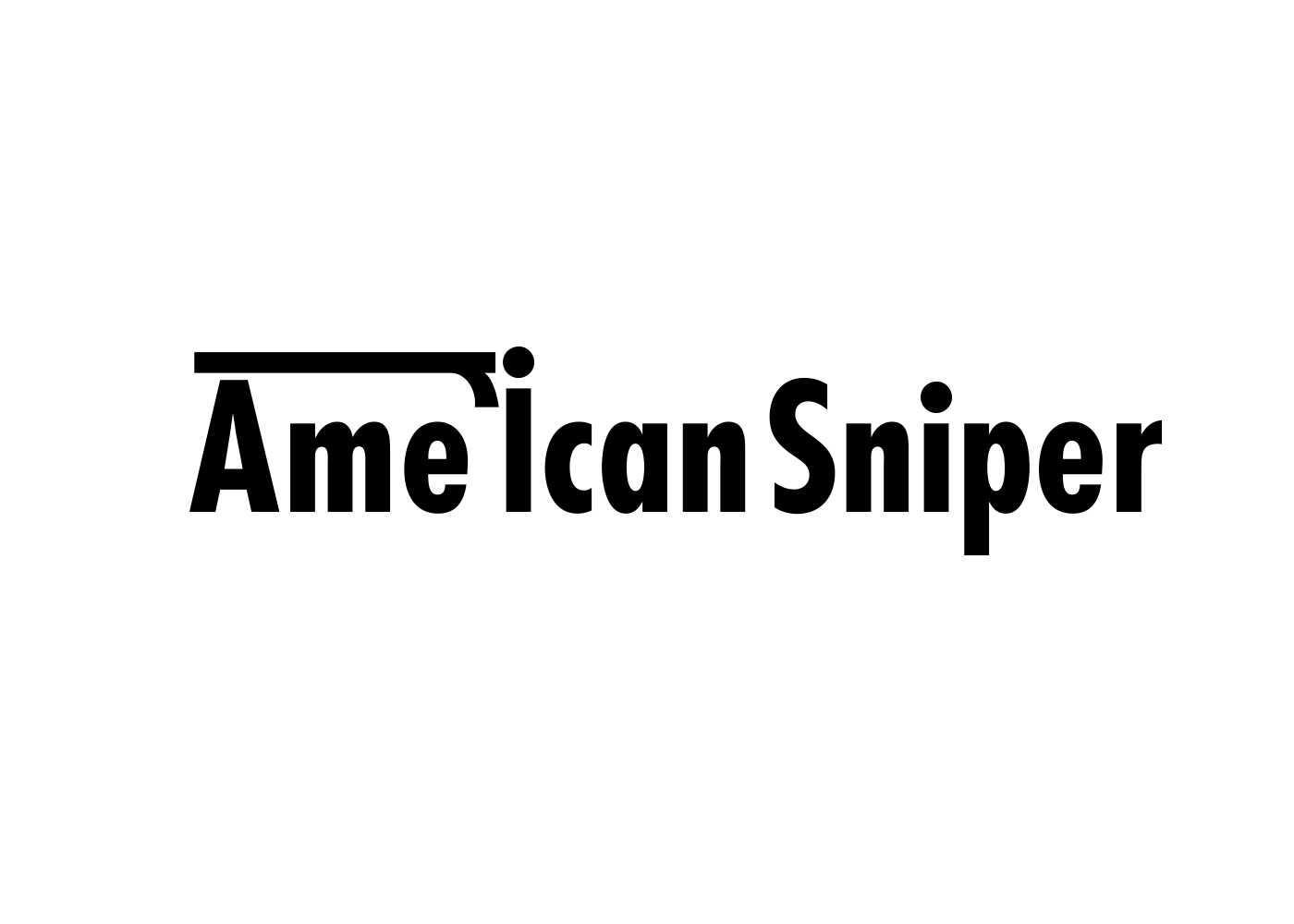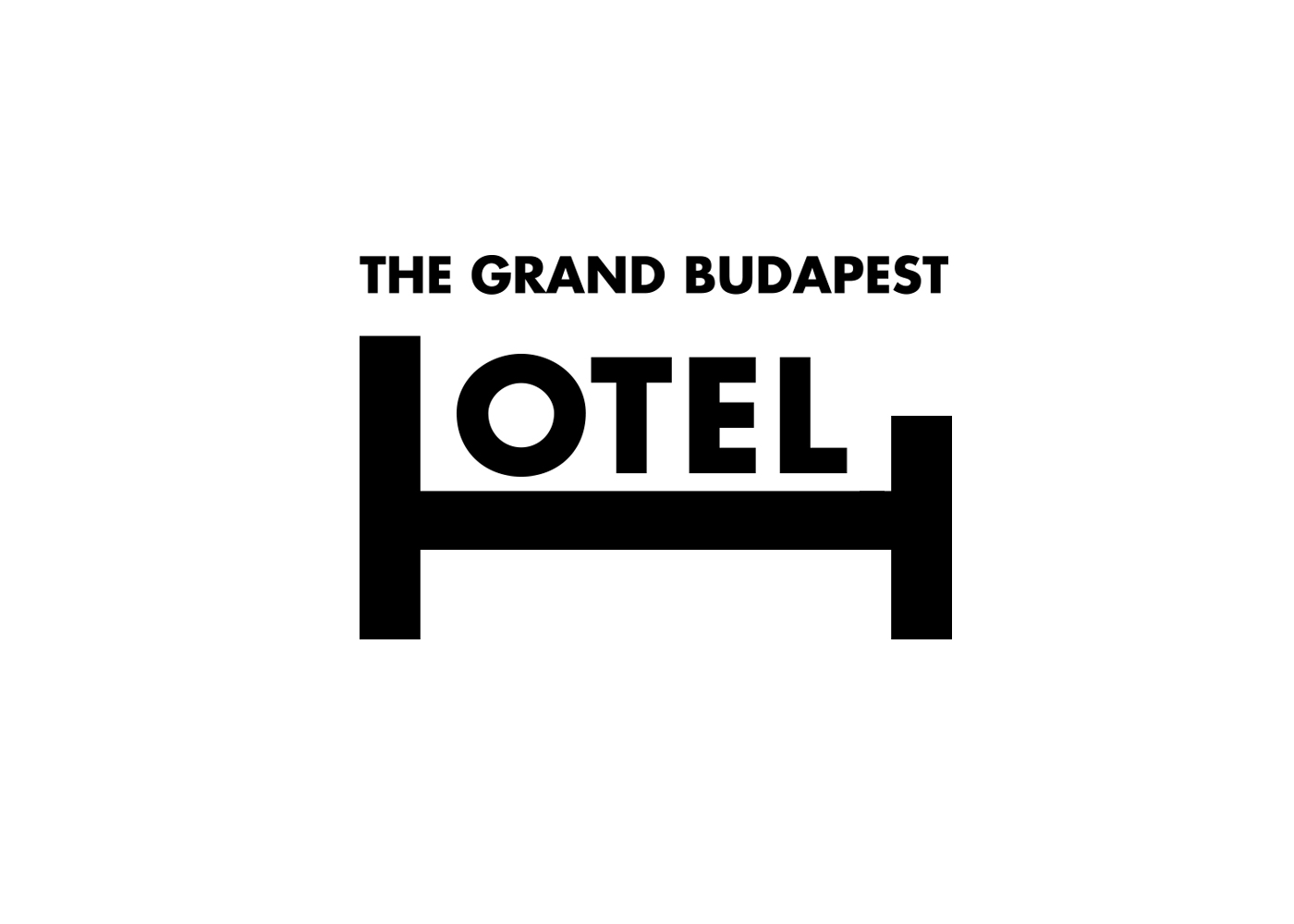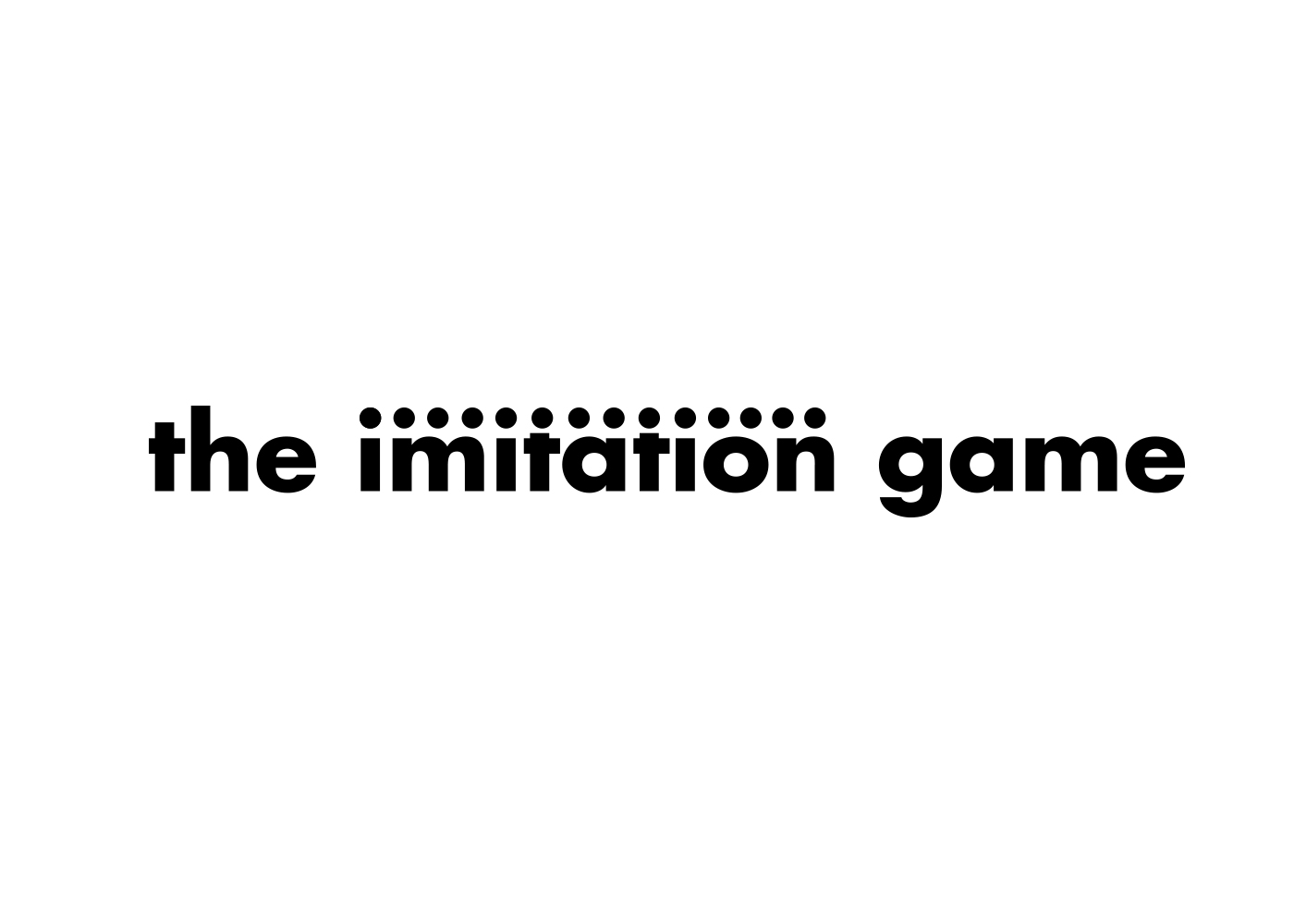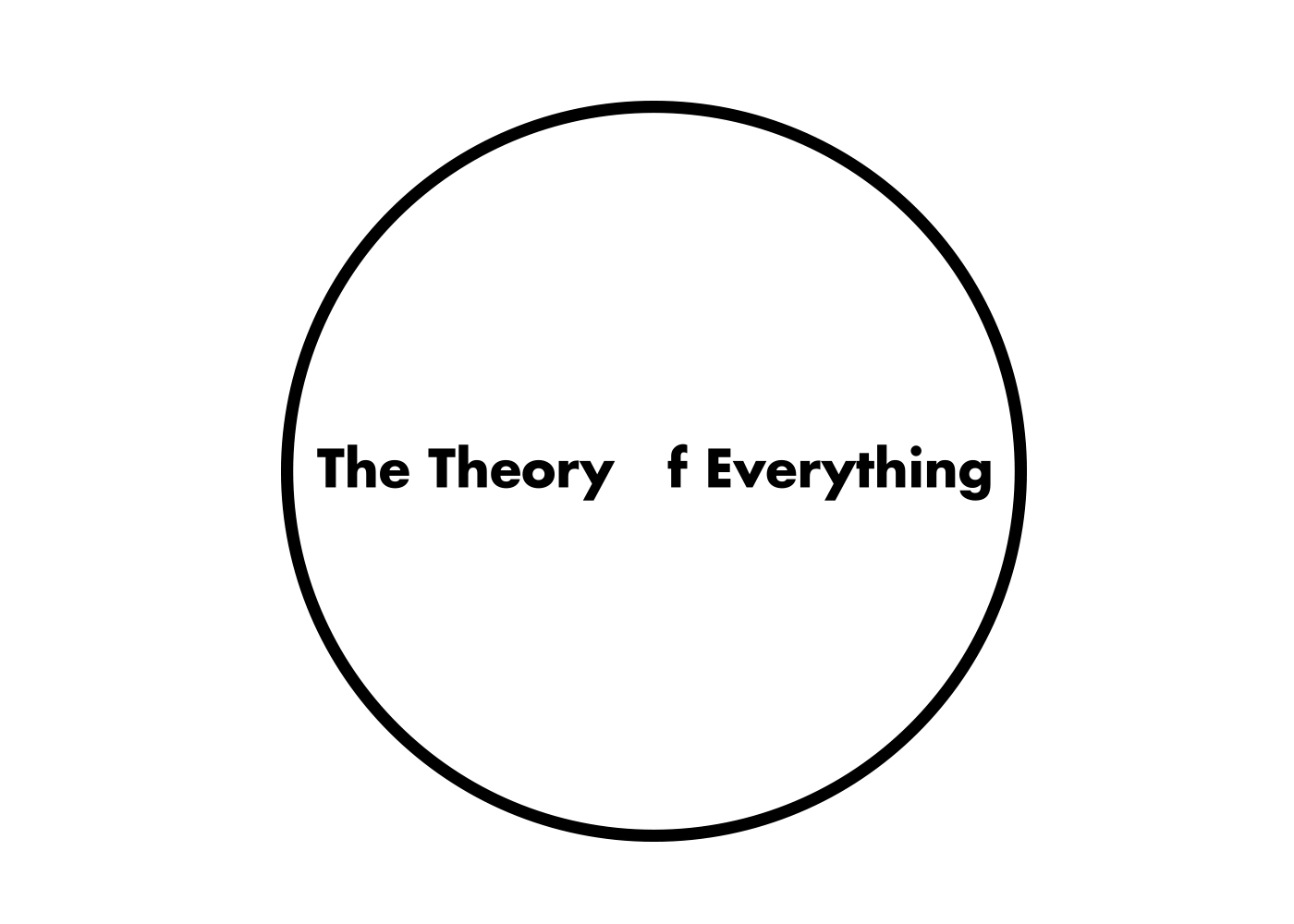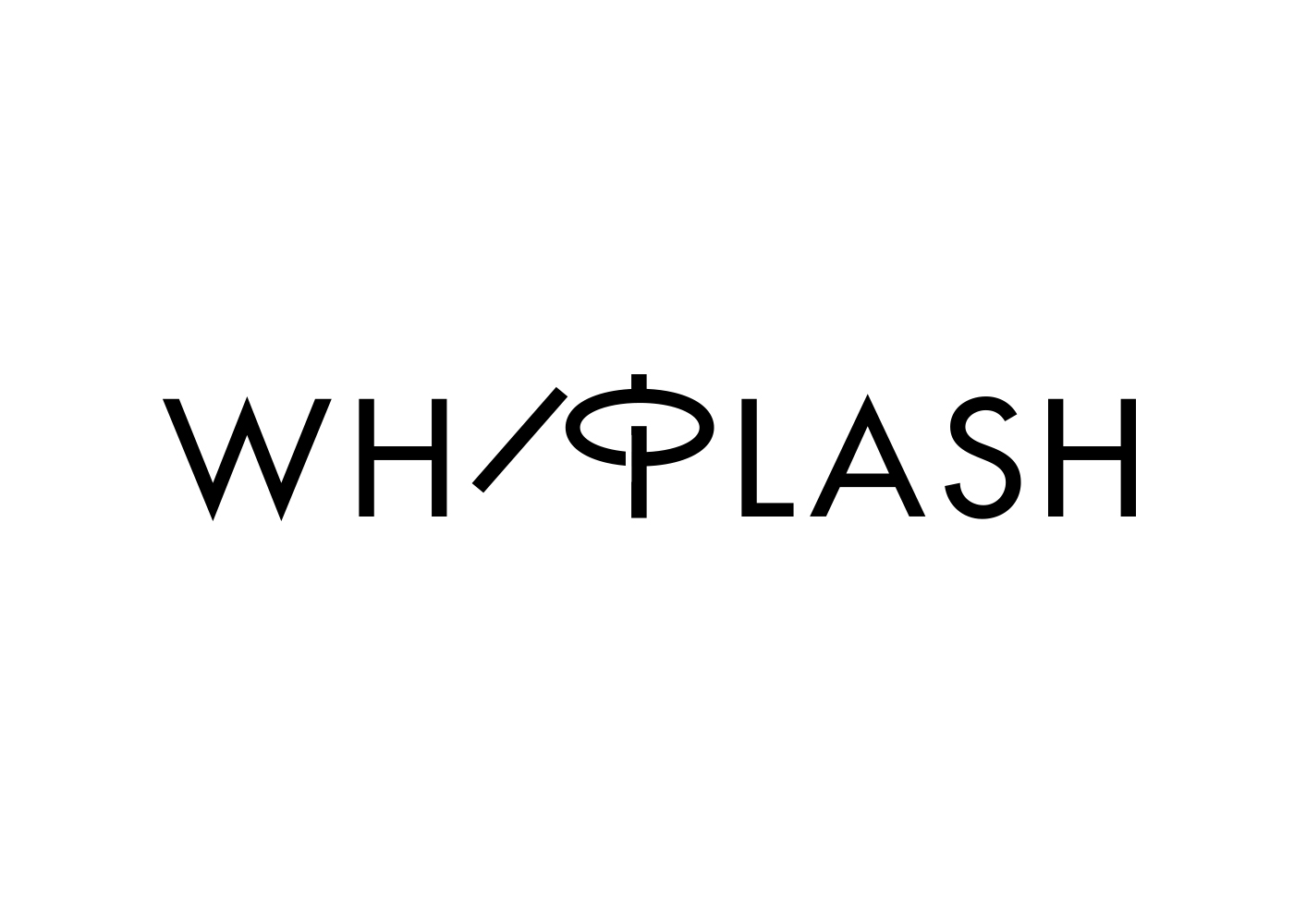
Tipografia dá pistas sobre temas tratados nos filmes indicados ao Oscar
Criação é do designer Ji Lee
Para muitos, a tipografia está entre os elementos mais fascinantes do design. Prova disso está em Word as Image, criado pelo designer Ji Lee. Acostumado a brincar com as palavras, explicando seus significados com a tipografia, ele repete a fórmula em uma série especial de seu projeto, dando pistas sobre o tema/roteiro dos indicados ao Oscar de melhor filme. Birdman, que levou a estatueta este ano, abre o post acima.
Ao Huffington Post, Lee contou que é um grande fã de cinema, e logo após premiação se desafiou a transformar os oito indicados a melhor filme em imagens tipográficas. Apesar de não ter tido problemas com a maioria, o designer revelou que ficou “empacado” com Selma e Whiplash, mas que com sugestões de um amigo, conseguiu completar o trabalho. TheoryOfEverything ImitationGame Whiplash GrandBudapest AmericanSniper Boyhood Selma